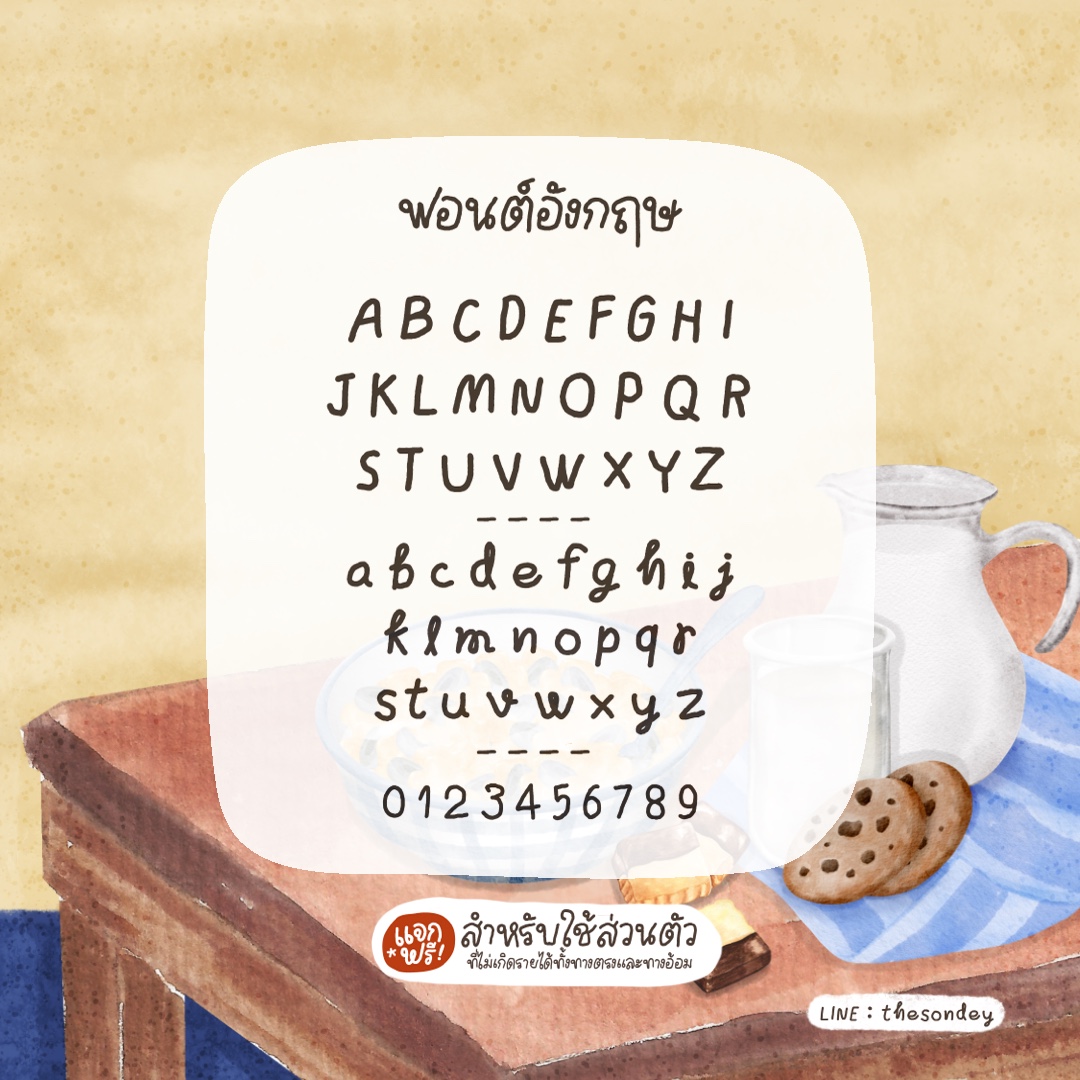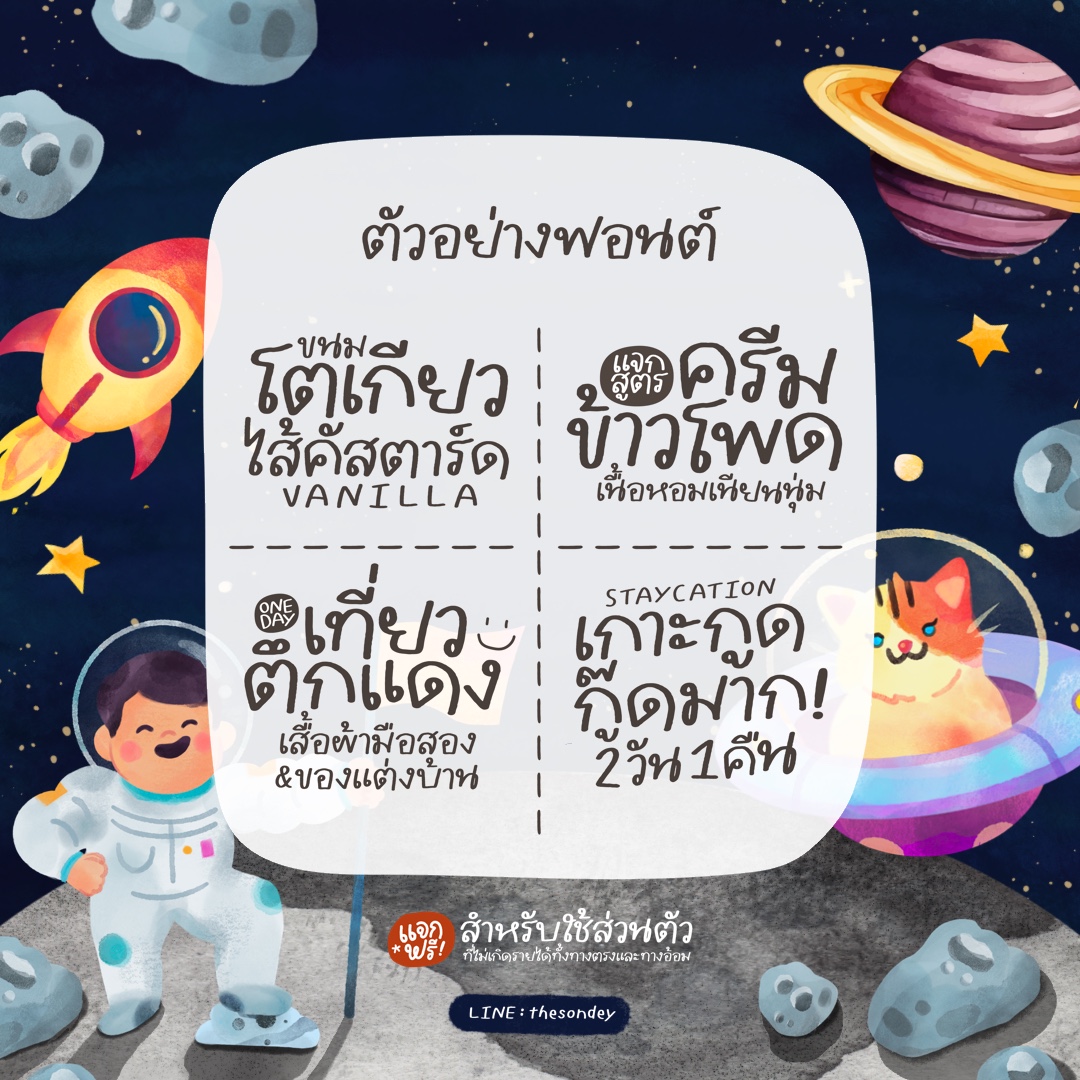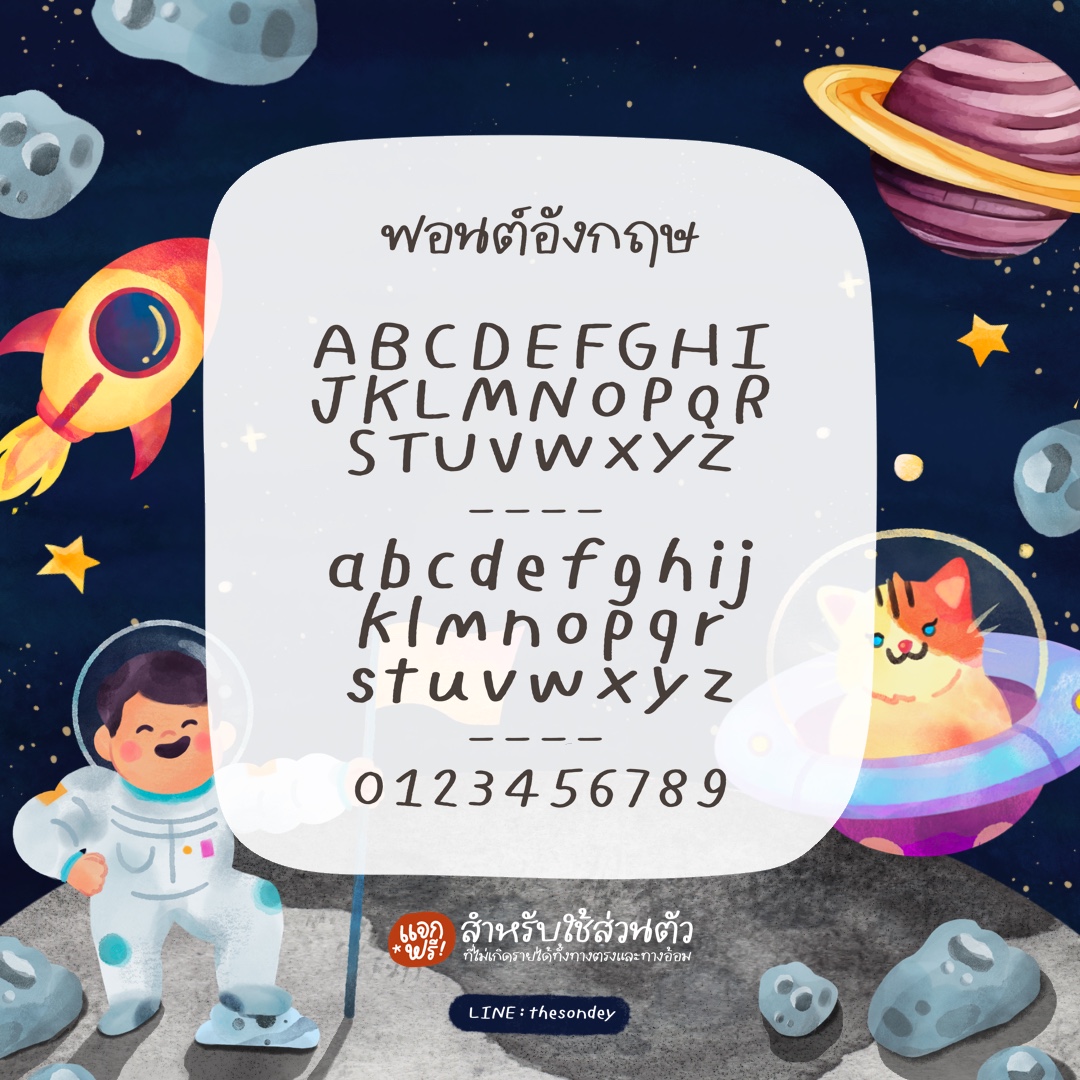
ฟอนต์ค็อกเทล (TCS4Cocktail)
เส้นหนา ปลายตัด ทรงเหลี่ยม
เหมาะทำหัวข้อสั้นๆ กระชับๆ
นูร่านิอันยา (Nura nianya)
ฟอนต์ลายมือ  ฟอนต์ลายมือมีหัว  มีด้วยกัน  3 น้ำหนัก  คือ บาง ปกติ หนา
ฟอนต์เต้าหู้ (TCS4Taohu)
ตัวอ้วนหนา ปลายตัด
เหมาะทำหัวข้อสั้นๆ กระชับๆ
ฟอนต์ ไข่มุก (BF khaimuk )
ปรับสระเรียบร้อย พร้อมใช้งานทุกแพลตฟอร์มที่รองรับฟอนต์